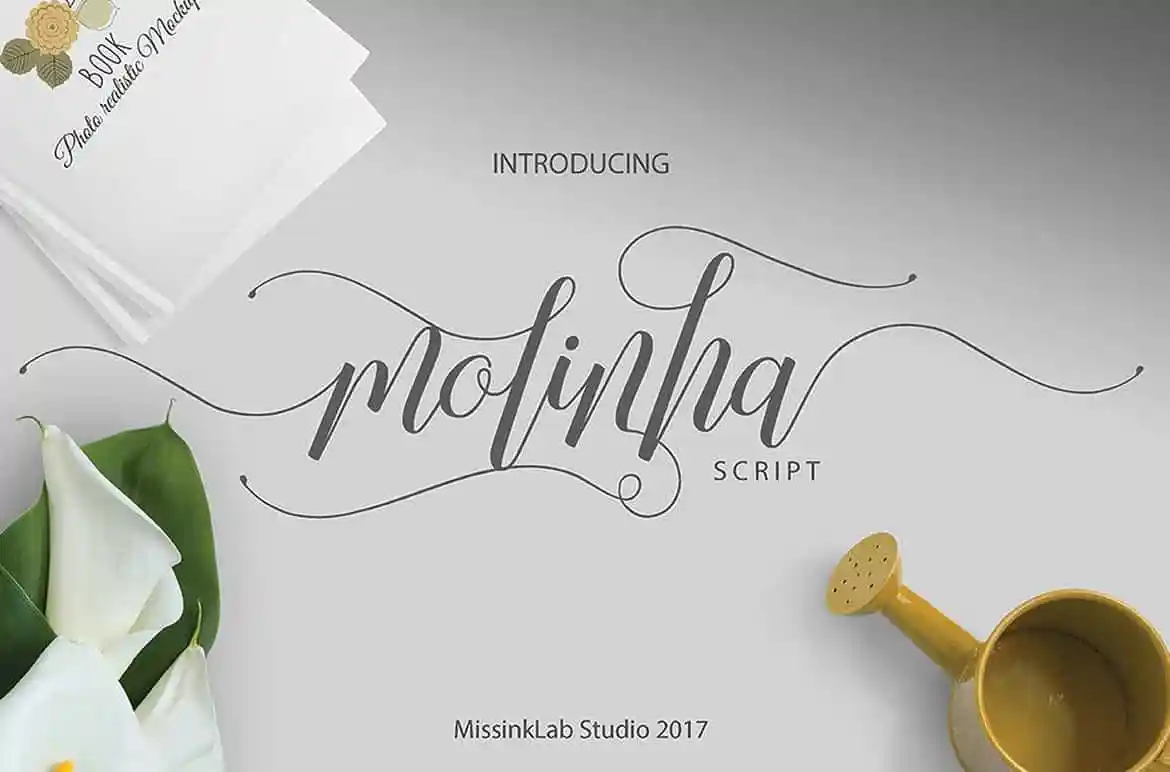
Molinha é uma tipografia criada para projetos design atuais e futuros que buscam um equilíbrio entre modernidade e clássico. Inspirado na escrita à mão, essa fonte é simples e suave, perfeita tanto para iniciantes quanto para profissionais. Seu estilo script moderno e clean está em alta demanda atualmente, especialmente para projetos como casamentos, convites de aniversário, cartas de agradecimento, panfletos, cartões de visita, citações, cabeçalhos de blog, marcação, logotipos, moda, roupas, cartas e papelaria. Molinha é perfeito para criar um design que atenda às mais variadas necessidades e objetivos gráficos. Com apenas alguns cliques, transforme suas ideias em criações únicas e impactantes.